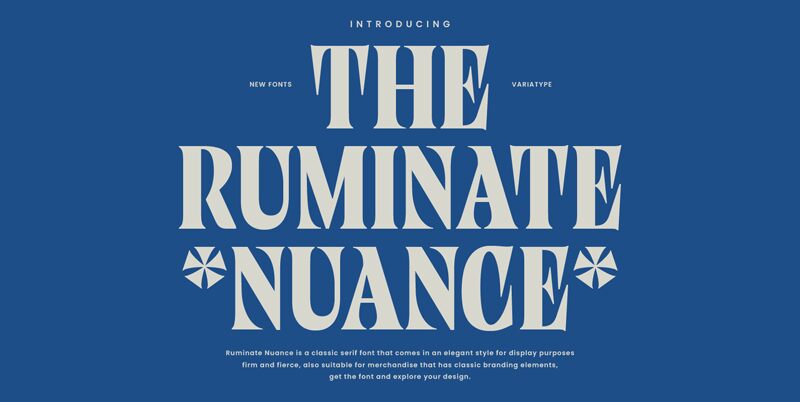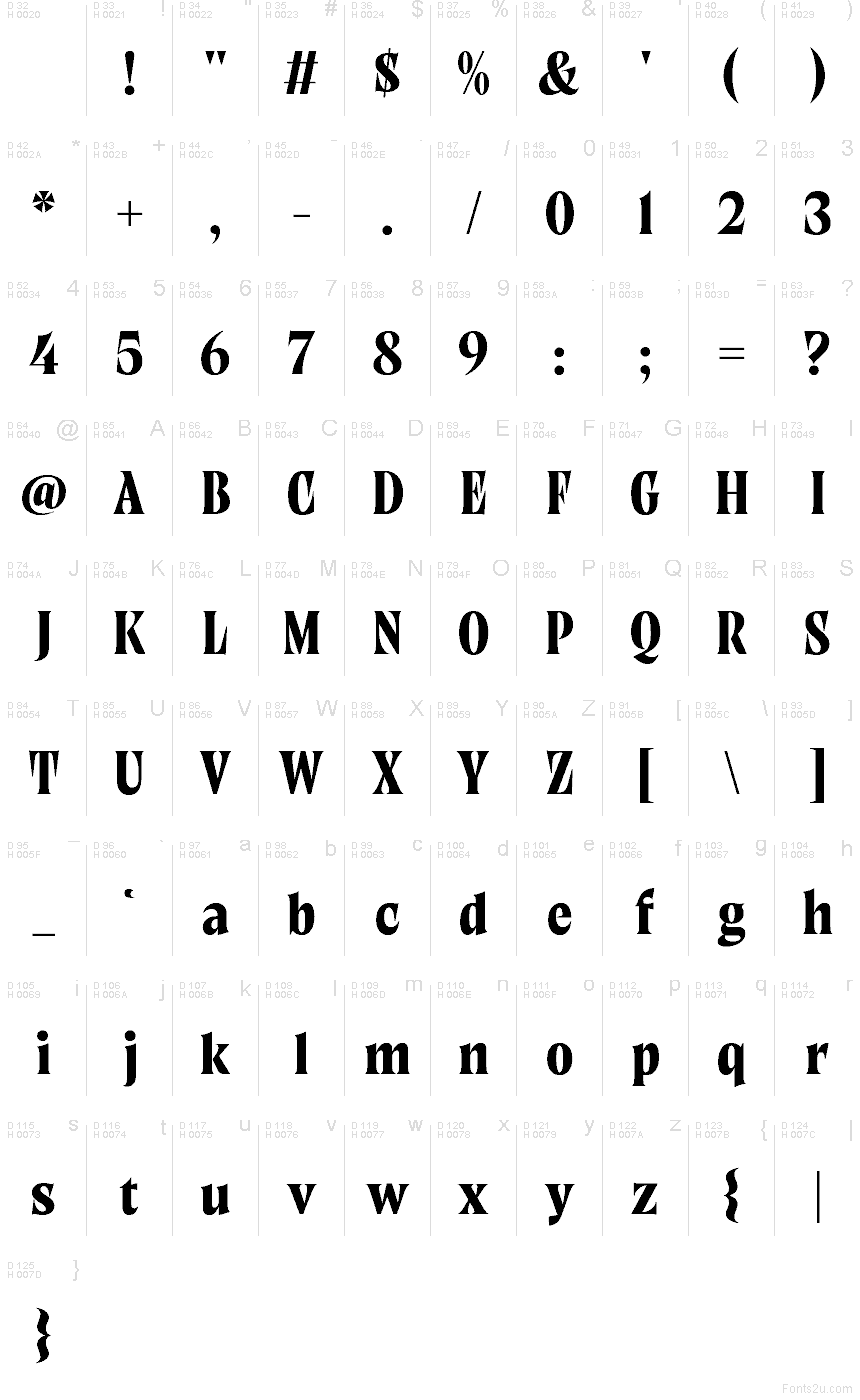
Ruminate Nuance von Variatype ist eine kostenlose, kontrastreiche Serifenschrift aus dem Jahr 2024 mit dem Flair eines Fashion-Editorials. Ihre Buchstaben kombinieren hohe, schlanke Formen mit scharfen, skulpturalen Verbindungen und eleganten Schwüngen. Das verleiht der Schrift einen ausgewogenen, fast dramatischen Rhythmus, der eher edel als überladen wirkt.
Damit eignet sie sich perfekt für Magazin-Titel, Beauty-Verpackungen, Buchcover, Boutique-Branding und Title Cards, bei denen es auf Präsenz ankommt. Als Free Font macht sie auch bei Zitat-Boxen, Cover-Lines und Monogrammen eine gute Figur, da die spitz zulaufenden Striche und die schmale Silhouette für ein klares, zielgerichtetes Schriftbild sorgen.